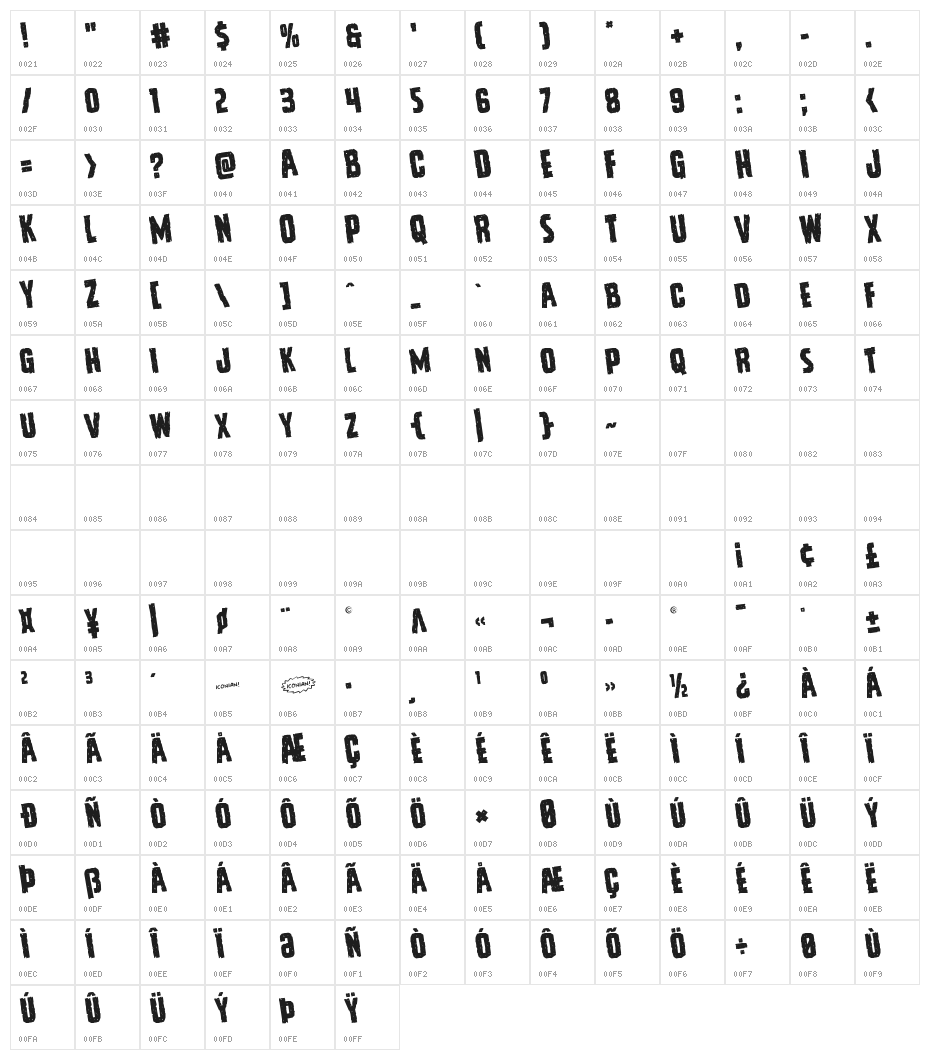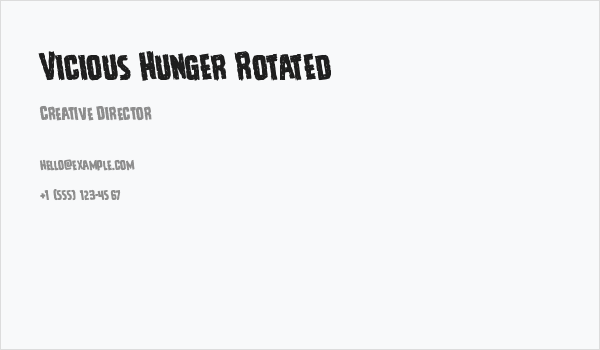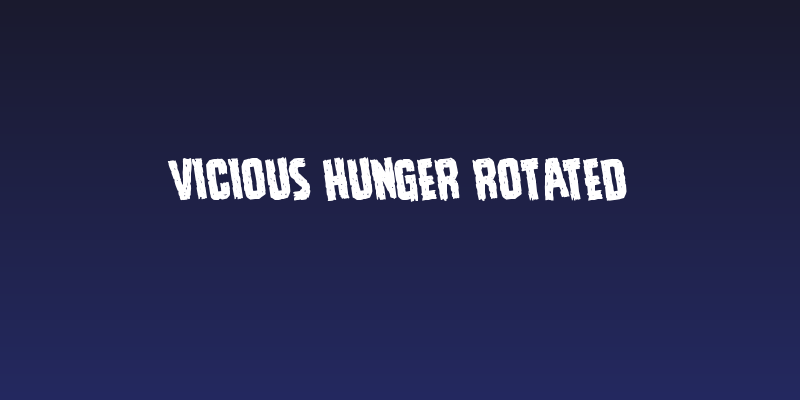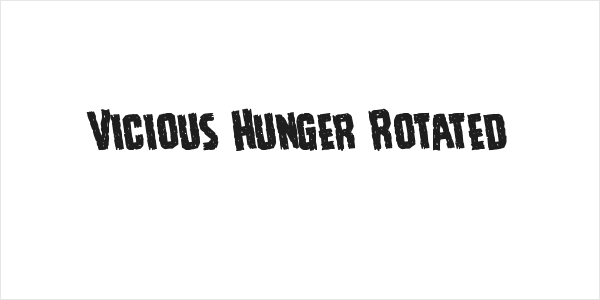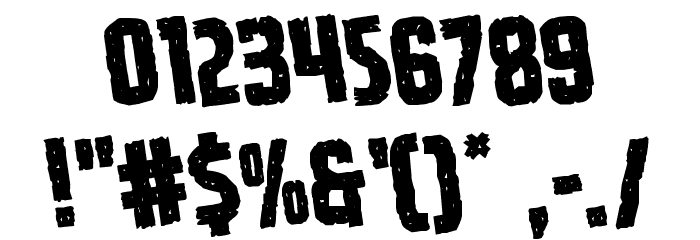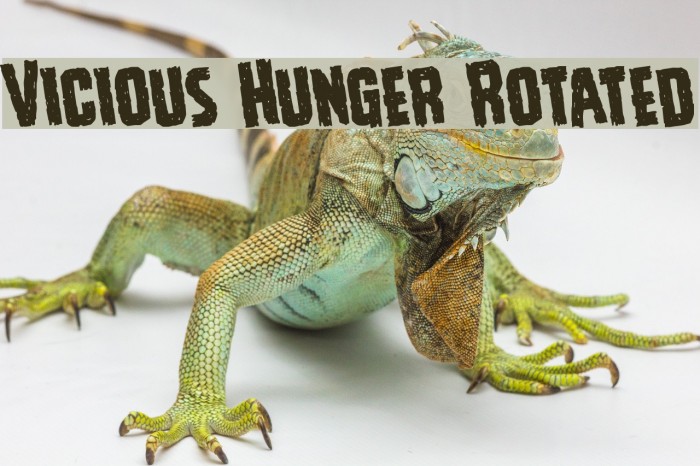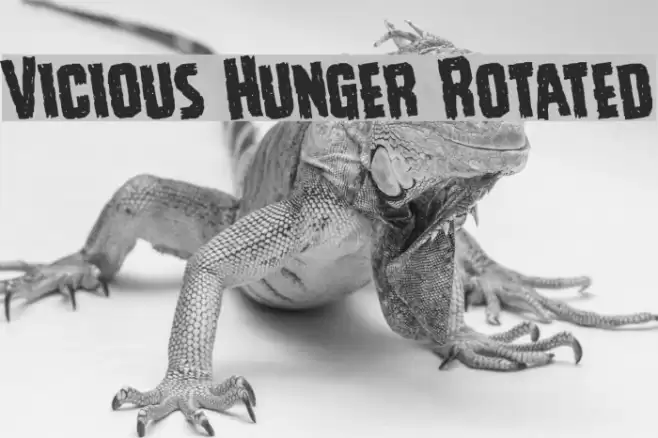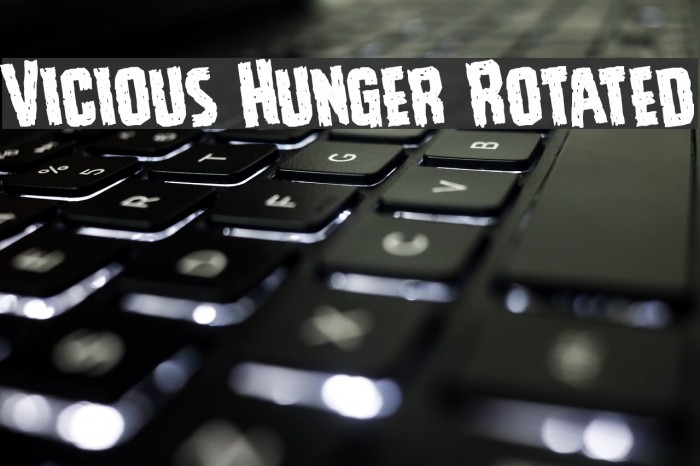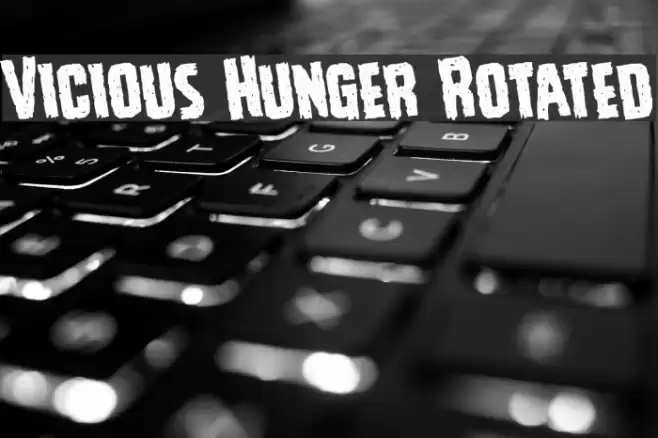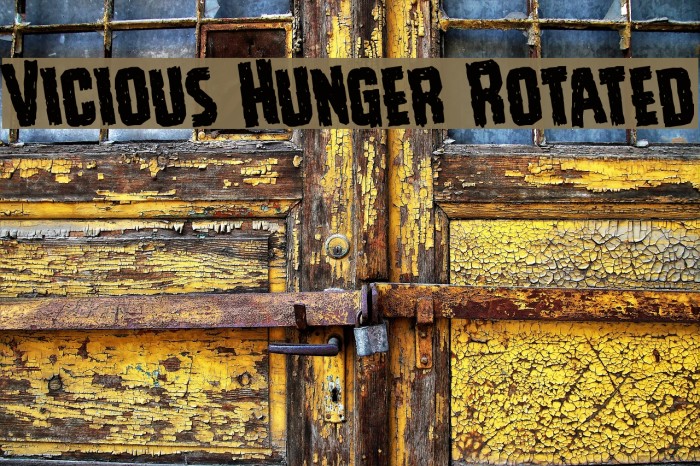
Vicious Hunger Rotated Font
| 全体的なスタイル | Urban, Edgy, Distressed |
| おすすめプロジェクト | Ideal for album covers, streetwear branding, posters, and event flyers. |